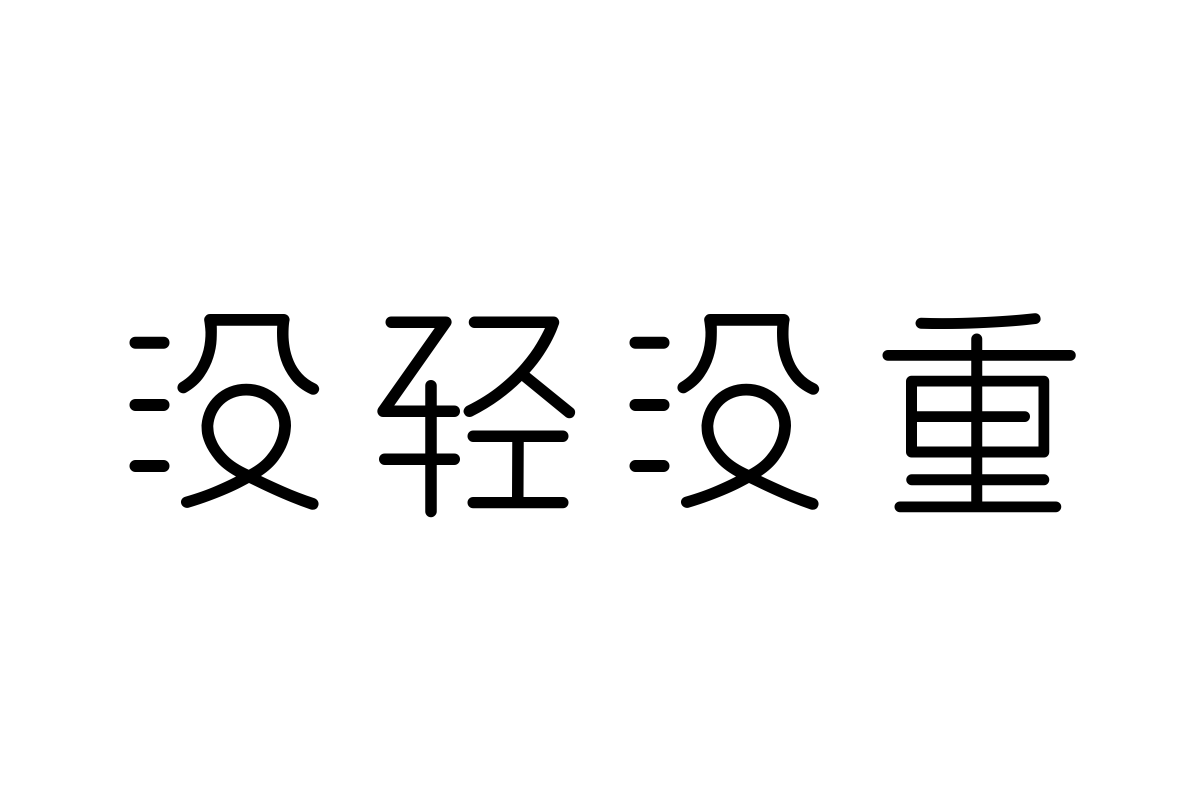
汉仪游园体是一款具有现代感和艺术感的中文字体,适用于各种设计项目,如广告、标志、海报、网页等。它的设计灵感来源于自然景观,包括树木、花朵、草地等元素,给人一种轻松、舒适的感觉。
汉仪游园体的笔画流畅,结构简洁,易于阅读和识别。它的特点是字形圆润饱满,线条柔和,给人一种温馨、亲切的感觉。同时,该字体也具有一定的艺术感,适合用于创意设计。
汉仪游园体的特点:
1. 简约风格:汉仪游园体的设计简洁大方,没有过多的装饰元素,适合用于各种设计项目。
2. 易读性:该字体的字形圆润饱满,线条柔和,易于阅读和识别。
3. 艺术感:汉仪游园体的笔画流畅,结构简洁,具有一定的艺术感,适合用于创意设计。
5. 可定制性:汉仪游园体支持自定义字重和字号,用户可以根据自己的需求调整字体的视觉效果。